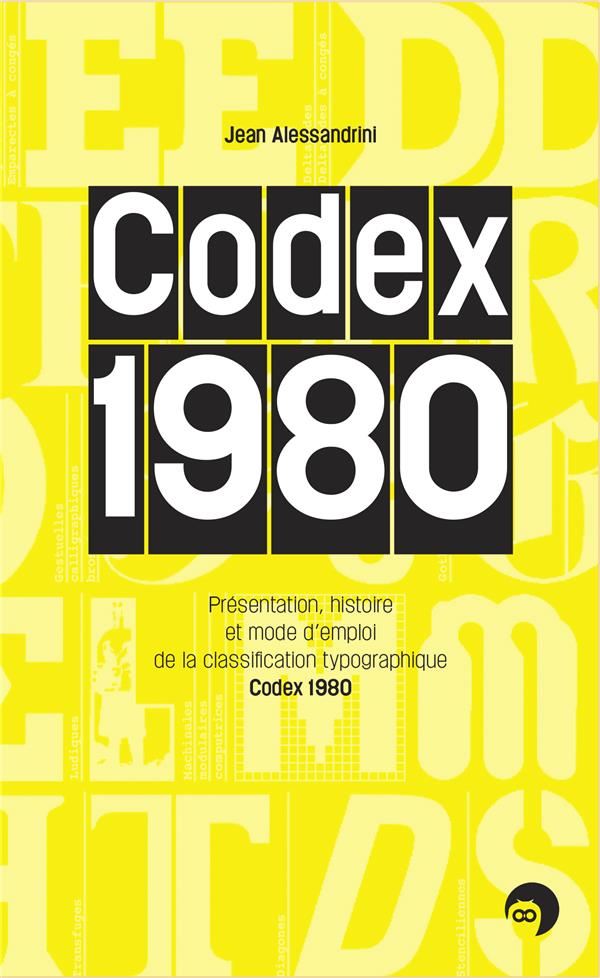
CODEX 1980
Livre neuf. Codex 1980. Jean Alessandrini, illustrateur et écrivain, a toujours aimé les alphabets : depuis ses études d'art à l'école Corvisart, il les découpe et les collectionne, pour pouvoir mieux s'en resservir plus tard (quand il ne les dessine pas).
À la fin des années 1970, il se retrouve donc avec des centaines d'alphabets et cherche à les classer, mais trouve la classification en vigueur, dite Vox-Atypi, peu performante. Il décide donc de créer son propre système, tel un entomologiste... Et présente sa classification, baptisée Codex 1980 par un François Richaudeau en forme, au grand public, ce qui lui vaudra une impressionnante volée de bois vert de la part des anciens compagnons de Lurs.
Cet ouvrage retrace l'histoire et les principes de cette classification controversée mais dont on reparle maintenant avec beaucoup d'intérêt et qui est même enseignée aujourd'hui dans certaines écoles. Un manuel très pratique pour s'y retrouver dans le dédale de la profusion typographique.